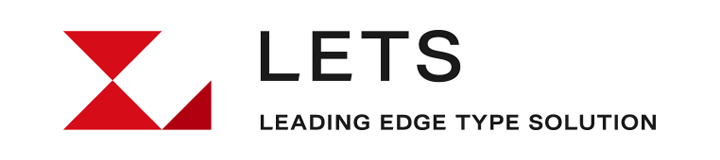
現在ご提供中のフォントだけでなく、新たにリリースされるフォントも使えます。
充実の検索機能でフォントを直感的に探せます。
使うフォントはON、使わないフォントはOFF。ボタンひとつで管理できます。
気に入りのフォントをリスト化し、PC間で同期。リスト単位でのアクティベートも可能です。
複数メーカーの高品位でバラエティ豊かなフォントがすべて使用できる年間定額制フォントサービスです。
バリエーション豊かなラインナップで、日本語、ハングル、簡体字、繁体字、タイ、ヘブライなどの各種フォントを提供しています。
130年の歴史を誇る Monotype 株式会社の豊富なフォントライブラリーからセレクトされたおよそ9,000書体の欧文/多言語フォントを年間契約で利用できる年間定額制フォントサービスです。Helvetica®、Frutiger®、Optima®など世界的に有名かつ高品位な欧文フォントや、豊富な多言語フォントをご利用できます。
楷書、行書やデザイン系まで、クオリティ高い毛筆書体を取り扱う株式会社昭和書体の各種フォントが年間契約のフォント導入システム「LETS」形式でご使用いただけるプログラムです。
書籍や広告からデジタルコンテンツまで幅広い人気を誇る株式会社昭和書体の毛筆書体を、自由にそして安心してお使いいただけます。
多くの実績と高いクオリティを誇る株式会社イワタの各種フォント『イワタコレクション』が年間定額制フォントサービス「LETS」の形式でご使用いただけるプログラムです。
活字時代からの書体開発の歴史と書籍からユニバーサルデザイン(UD)まで多くの使用実績を誇る、株式会社イワタのイワタフォントライブラリーを「イワタコレクション」として、自由にそして安心してお使いいただけます。
60年以上の歴史を持つ株式会社モトヤの各種フォント『モトヤコレクション』が年間定額制フォントサービス「LETS」形式でご使用いただけるプログラムです。「可読性の良さ」と「文字の美しさ」を特徴とし、各種印刷物やWeb・Androidスマートフォンなどに広く採用されている株式会社モトヤのフォントライブラリーを「モトヤコレクション」として、自由にそして安心してお使いいただけます。
韓国市場にて最も使用され、近年では書体開発だけではなく書体と関連したデザインソリューションを展開しているフォントメーカーのYoonDesign Group Inc.の各種フォントが年間契約のフォント導入システム「LETS」形式でご使用いただけるプログラムです。書籍や広告からデジタルコンテンツまで幅広い人気を誇るYoonDesign Group Inc.の韓国語書体を、自由にそして安心してお使いいただけます。
中国市場でトップシェアを誇るフォントメーカー方正株式会社(ほうせい)の中国語フォントを年間定額制フォントサービス『方正 LETS』として提供しています。方正 LETSは、中国本土で使われている国家標準(GuoJia-BiaoZhun)規格であるGB2312、GBKに準拠したMac用TrueTypeフォントとWindows用TrueTypeフォントをご用意しております。